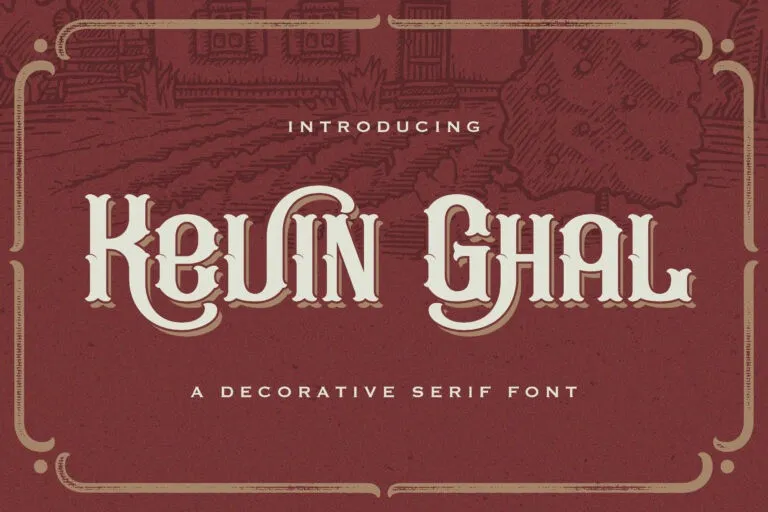
A fonte Kevin Ghal é uma fantasia visual vintage com um toque nostálgico que ainda mantém um aspecto luxuoso na concepção moderna. Inspirada nas estampas antigas, esta tipografia apresenta formas românticas e ousadas, projetadas para destacar em designs tanto clássicos quanto contemporâneos. Seus detalhes cuidadosamente elaborados a tornam uma escolha irresistível para qualquer projeto que busque um toque autêntico de passado recente em seu design moderno ou sofisticado. Ideal para aplicativos como logotipos, selos e materiais de identidade visual, Kevin Ghal é uma fonte perfeita para designers buscando incorporar um aspecto vintage em seus projetos digitais atuais.